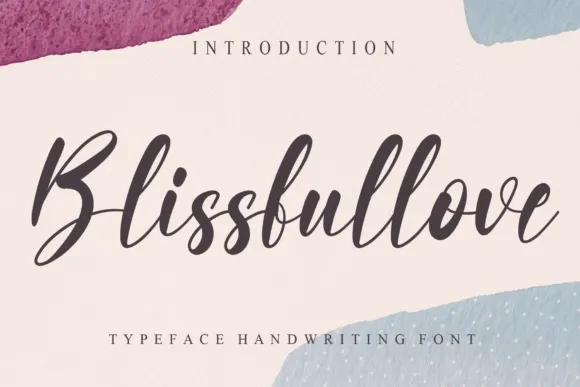
Esta fonte é uma mão-dupla amigável projetada para adicionar um toque alegre aos seus designs. Com seu estilo limpo e versatilidade, ela pode iluminar qualquer projeto de design que você faça. Seja você um designer experiente ou está apenas começando na arte da criação gráfica, essa fonte é ideal para explorar suas inúmeras variações alegres e divertidas. Prepare-se para ter muita diversão enquanto trabalha com Blissfullove Font. Experimente-a e veja como ela pode transformar seu trabalho em algo único e cheio de vida.